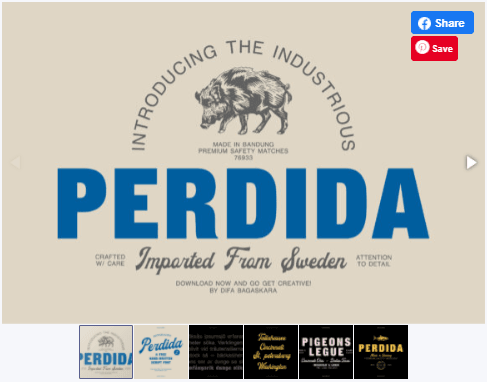
Perdida Font
Perdida - жирный и напористый дисплейный шрифт. Независимо от темы, этот шрифт будет невероятно полезен для вашей библиотеки шрифтов, так как он может улучшить любое творение.